Как различать основные и соединительные штрихи в буквах
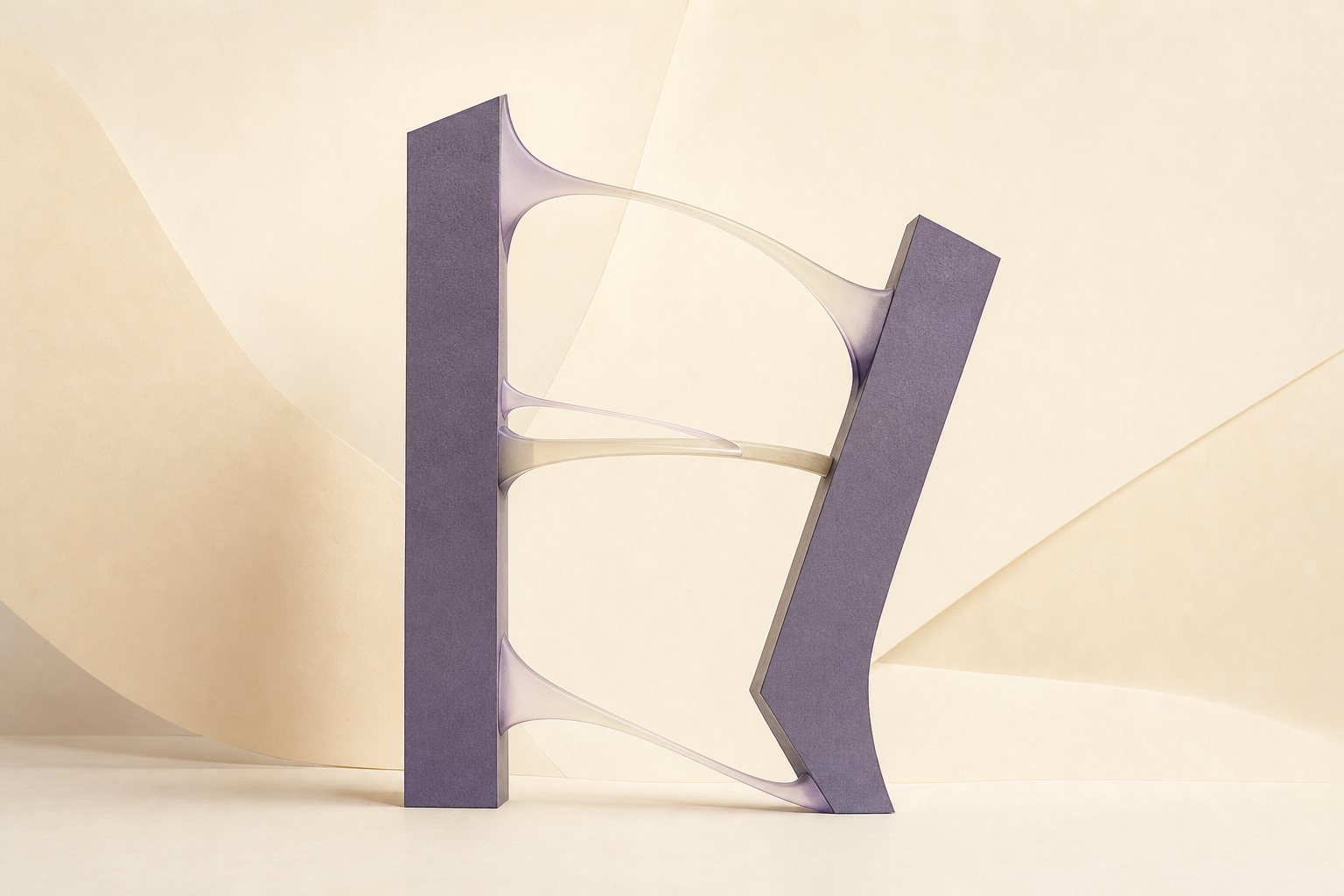
Основные и соединительные штрихи: короткий ответ
Основной штрих — главный несущий элемент буквы, который определяет её конструкцию, ширину и визуальный вес. Соединительный штрих связывает основные элементы между собой и часто выглядит тоньше или легче. В статье разберём, как находить эти части в кириллице и латинице, почему их нельзя определять только по толщине и как применять анализ при работе со шрифтом.
Что называют штрихом в конструкции буквы
Штрихом называют отдельный направленный элемент знака: вертикаль, горизонталь, диагональ, дугу или криволинейный участок. В совокупности штрихи образуют скелет буквы, её пропорции и характер. Когда дизайнер рассматривает знак, он оценивает не только контур, но и то, какие элементы несут форму, какие замыкают пространство, а какие обеспечивают переход между частями.
В учебном анализе шрифта основной штрих обычно связан с направлением письма и распределением контраста. В антиквенных гарнитурах это часто вертикальный или диагональный стержень, а соединительный штрих образует более тонкий переход, дугу или перемычку. В каллиграфии похожее различие связано с движением инструмента: сильный нажим даёт широкую линию, лёгкое движение — тонкую.
Как устроены основные штрихи
Основные штрихи формируют несущую схему буквы. Они задают вертикальный масштаб, общую ширину и устойчивость знака в строке. В букве Н такими элементами будут две вертикали, соединённые перекладиной. В букве А главную роль играют две диагональные опоры, а горизонтальная перекладина связывает их и разделяет внутреннее пространство.
У основных штрихов обычно есть заметные окончания, места присоединения и согласованный визуальный вес. Если один стержень сделать слишком узким, буква потеряет равновесие; если чрезмерно утяжелить его, знак начнёт темнеть в наборе. Поэтому при создании шрифта основные элементы сначала выстраивают как систему, а затем уточняют их кривизну, терминалы и контраст.
Вертикали, диагонали и горизонтальные опоры
Вертикальные стержни легко заметить в Н, П, Ш и большинстве строчных знаков с прямыми стойками. Диагонали становятся главными в А, Л, К, М, У и латинских V, W, X. Горизонтали чаще выступают как перекладины или основания, но в отдельных знаках могут влиять на ощущение веса сильнее, чем вертикали. Их роль определяется всей системой конкретного шрифта.
Как устроены соединительные штрихи
Соединительные штрихи объединяют основные части буквы в единый знак. Это могут быть перекладины, дуги, плечи, перемычки, выносные элементы и тонкие переходы между стержнем и округлой формой. В строчной кириллической н соединительная дуга связывает вертикальные стойки; в и диагональный ход соединяет элементы, создавая непрерывный ритм.
В контрастном шрифте соединение часто выглядит тоньше, потому что его направление или траектория предполагают меньшее давление инструмента. Однако это не универсальное правило. В гротеске с почти равномерной толщиной все линии могут иметь близкий вес, а различие между основным и соединительным штрихом проявляется через положение, функцию, кривизну и участие в формировании внутреннего просвета.
Дуги, плечи и перемычки в кириллице
У строчных н, п, т и похожих знаков соединительные элементы образуют плечи и дуги. Они влияют на серый тон строки: слишком тяжёлая дуга делает текст плотным, а чрезмерно тонкая визуально разрывает букву. В букве ж перемычки и диагональные пересечения нужно оценивать вместе: отдельные линии могут быть аккуратными, но их общий узел — слишком тёмным.
Почему толщины недостаточно для определения
Механическое правило «толстое — основное, тонкое — соединительное» работает только в шрифтах с выраженным контрастом и понятной каллиграфической моделью. В моноширинном или геометрическом гротеске толщина штрихов специально выравнивается. Тогда главным становится структурный анализ: какой элемент держит силуэт, какой связывает части, какой формирует просвет и направляет движение взгляда.
Есть и оптические поправки. Горизонтальная линия одинаковой математической толщины может казаться тяжелее вертикальной, а место пересечения двух диагоналей — темнее соседних участков. В профессиональном шрифтовом дизайне контуры корректируют не ради геометрической формулы, а ради равновесия в реальном наборе. Поэтому штрих следует проверять в словах, а не только в увеличенном знаке.
Практический алгоритм анализа буквы
Чтобы различить основные и соединительные штрихи, полезно временно отвлечься от названий гарнитуры и разобрать знак как конструкцию. Сначала определите базовую форму, затем найдите элементы, которые задают силуэт и несут визуальный вес. После этого проверьте, какие линии связывают опоры, создают внутренние просветы и обеспечивают переходы между прямыми и округлыми участками.
Вывод: анализируйте не линии, а систему
Основные штрихи создают каркас буквы, а соединительные связывают его части и формируют внутренний ритм. Надёжный способ различать их — учитывать одновременно функцию, направление, толщину, просветы и поведение знака в наборе. Используйте этот подход при анализе готовой гарнитуры или при разработке собственного начертания.